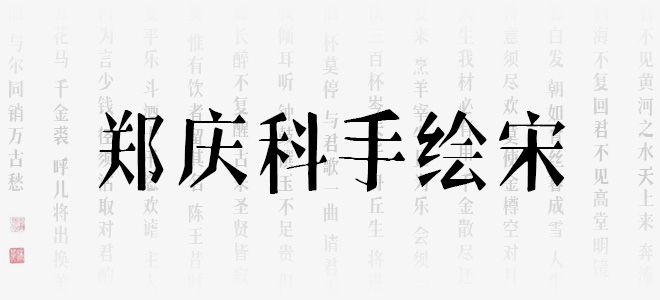
鄭慶科手繪宋是一款非常漂亮的藝術(shù)字體,生動活潑,趣味十足。適用于包裝設(shè)計、電商、品牌名稱、漫畫、影視綜藝、游戲、各類商業(yè)海報、戶外廣告標(biāo)題等設(shè)計領(lǐng)域。本字體基于中華人民共和國GB2312-80字符集標(biāo)準(zhǔn),采用TrueType和OpenType兩種格式,共收容漢字6763個,英文及標(biāo)點(diǎn)等常用字符814個。
鄭慶科手繪宋